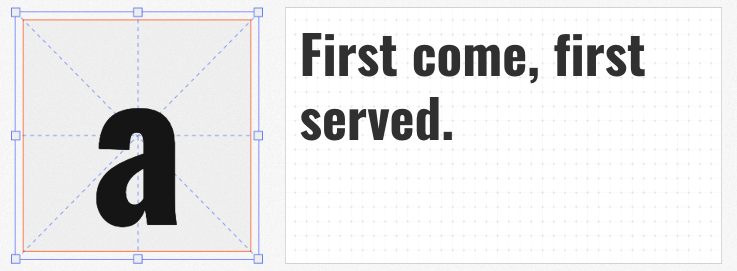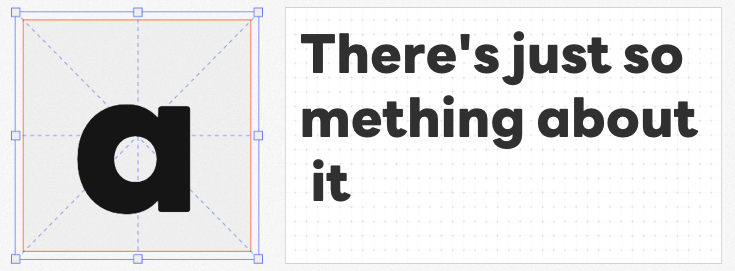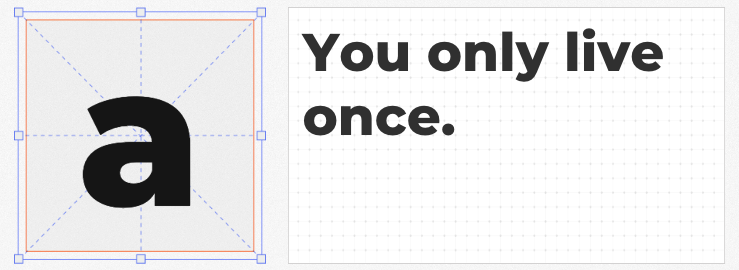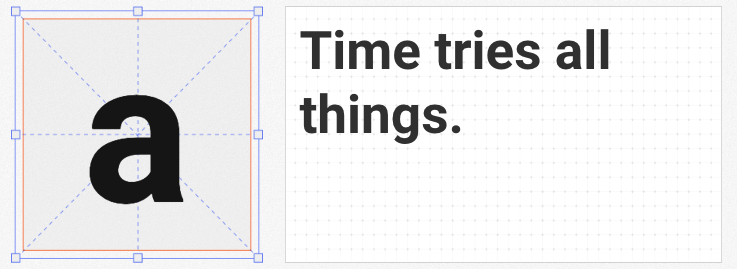
在商业设计中,选择一款兼具美感与实用性的免费字体至关重要。以下四款无衬线西文字体不仅免费可商用,更以独特的风格和广泛的适用性成为设计师的“万能工具箱”。
1. Montserrat ExtraBold
Montserrat的灵感源自南美蒙特塞拉特岛的建筑与自然景观,以简洁的几何线条和清晰的视觉层次著称。ExtraBold字重赋予其强烈的现代感,适合作为标题或强调文字,在海报、品牌标识中能瞬间抓住眼球。其略带圆角的细节处理,让硬朗的无衬线风格多了几分亲和力,尤其适合科技、旅游或生活方式类设计。
2. Oswald Bold
基于经典“交替哥特式”字体改造的Oswald,通过像素网格适配技术,成为数字时代的理想选择。Bold字重保留了复古字体的纵向张力,同时优化了小尺寸下的可读性,非常适合网页标题、移动端界面或长文本段落。其窄字幅设计还能有效节省空间,是响应式布局的得力助手。
3. LINE Seed Sans ExtraBold
由LINE联合多国团队开发的这款企业字体,覆盖日、韩、英、泰四语,日文字符多达9354个,堪称亚洲市场的“全能选手”。ExtraBold字重以极简的笔画和均匀的负空间,确保多语言混合排版时的视觉统一性。无论是APP界面、社交媒体海报还是跨国品牌物料,都能轻松驾驭。
4. Roboto Bold
作为Android系统的默认字体,Roboto以“机械精准”与“人文温度”的平衡闻名。Bold字重强化了字体的结构感,同时通过微妙的笔画弧度避免生硬感,适合需要传递专业感与科技感的场景,如数据可视化、产品手册或企业报告。其开源特性更让设计师无需担心版权风险。